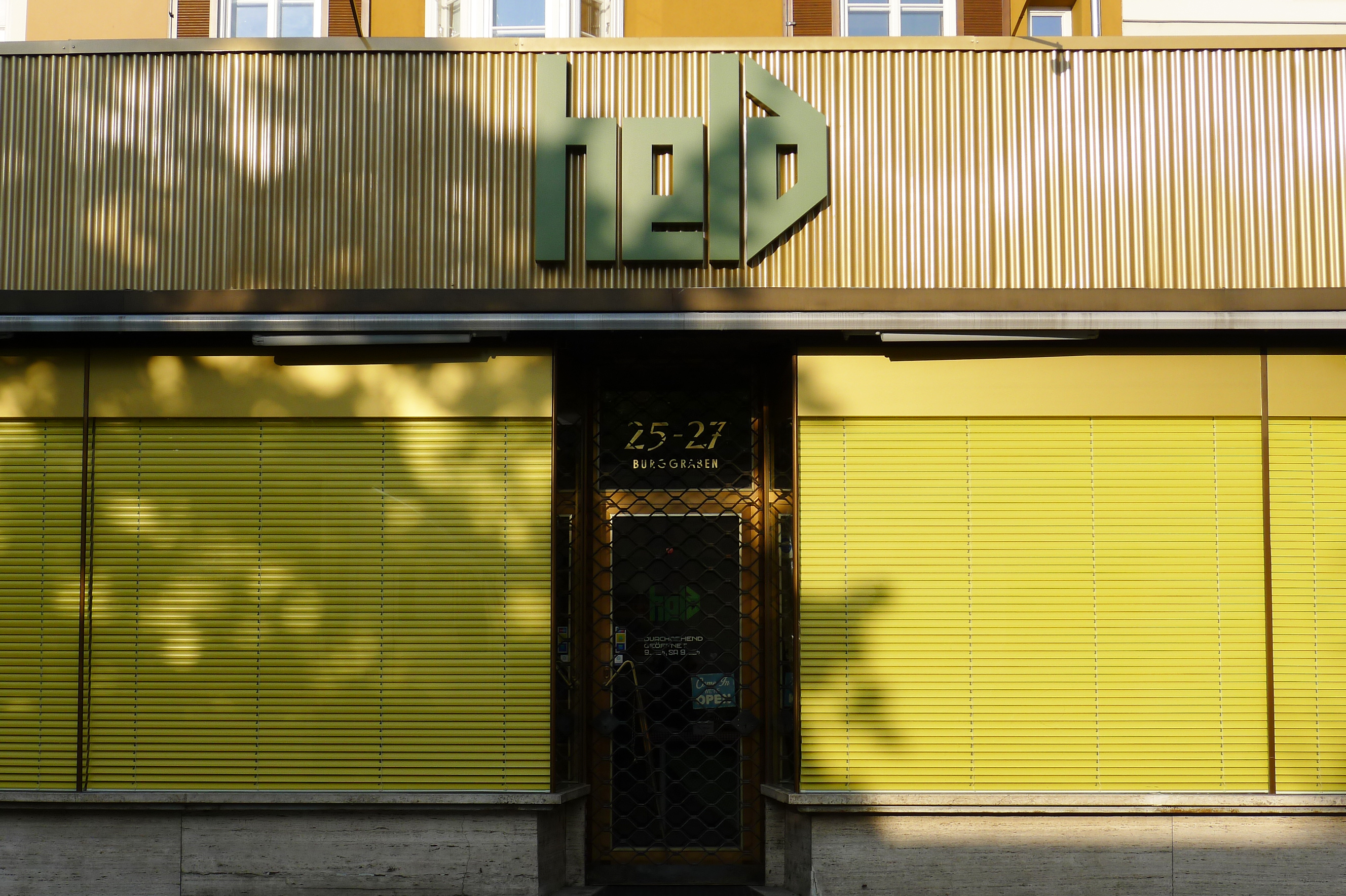
Hutmanufaktur Held
Der Schriftzug der Firma Held prägt den Franziskanerplatz schon seit Jahrzehnten. In seiner radikal reduzierten, nur aus Polygonen bestehenden Form wirkt er immer noch modern – folgte doch ihre Gestalterin, Elisabeth Mittermayr, den Notwendigkeiten, die an die Prägnanz eines Schriftzuges gestellt werden. Sie ist die Tochter von Arthur Zelger, einem der bekanntesten Gebrauchsgrafiker Tirols. Aufgewachsen im Arbeitsumfeld ihres Vaters hat sie lange Jahre in seinem Atelier mitgearbeitet. Bis heute steht sie in Kontakt mit Kunden aus dieser Zeit, wie z.B. dem Hotel Central, dem Möbelhaus Kranebitter, der Axamer Lizum und eben auch der Firma Held. Die Unternehmer, die hinter diesen Firmen stehen, erkennen die Wertigkeit der Arbeiten und haben so manchen "übereifrigen" Modernisierungsversuch in der beginnenden Ära es Desktop-Publishing, in dem ganz nach dem Motto "anything goes" gearbeitet wurde, abgewehrt. Wenn man bedenkt, dass viele weltweit bekannte Logos (CocaCola, Ford) schon über 100 Jahre alt sind, eine nachzuvollziehende Vorgangsweise. Übrigens: auch der Schriftzug im Inneren des Geschäfts („Modesalon“) ist sehenswert!